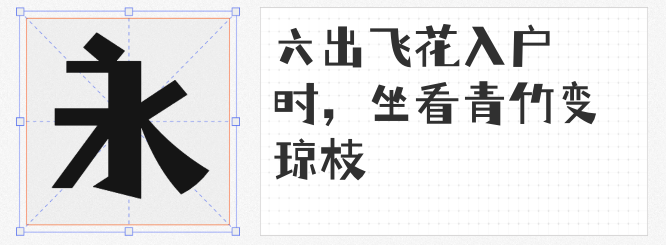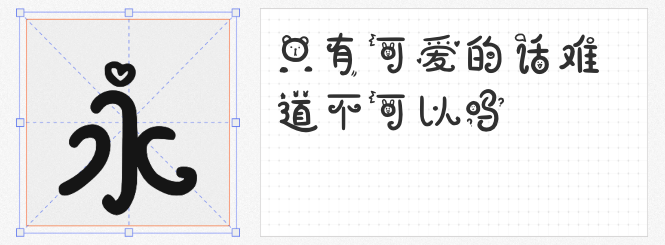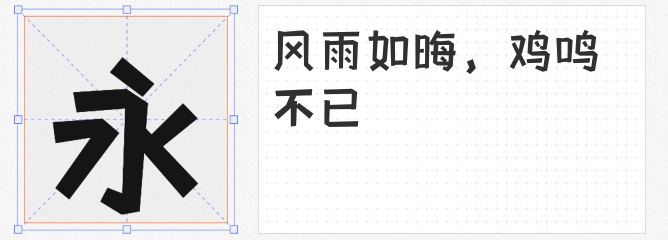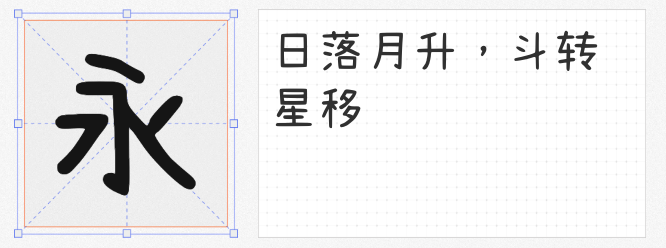
在追求个性与趣味的设计领域,一款灵动的字体往往能成为视觉焦点。今天为你精选四款自带可爱BUFF的免费商用创意字体,它们或古灵精怪,或软萌讨喜,轻松为设计注入鲜活生命力。
1.摄图摩登小方体
这款由摄图网与iFonts联袂打造的公益字体,将科幻片的未来感揉进黑体基因。方正笔画中暗藏太空舱般的几何细节,负形空间经过精妙切割,如同宇航员头盔的透明面罩,让文字既稳重又不失呼吸感。粗度适中的笔画既能驾驭电商大促的霓虹灯效,也能化身美食菜单的可爱招牌,是穿梭于现实与未来的设计多面手。
2.仓耳小丸子
当字体开始"表演",设计便成了游乐场。仓耳小丸子用夸张的粗细对比打破常规,某些笔画突然"叛逆"地歪斜,字间距也任性缩放,仿佛字体在纸面上跳踢踏舞。这种打破秩序的天真感,特别适合儿童绘本、文创周边等需要"不规则快乐"的场景,让观者一眼沦陷于它的古灵精怪。
3.千图小兔体
设计师将软萌兔耳化作笔画装饰,每个字都像是会跳动的棉花糖。免费下载的福利标签,让它成为独立设计师的宠儿——从奶茶店招牌到少女风海报,圆润线条自带甜蜜气息。最妙的是藏在小兔元素里的彩蛋:放大细看,某些笔画里藏着胡萝卜图案的负形惊喜。
4.cjkFonts全濑体
深度学习赋予这款字体"七十二变"的功力,既保留濑户体的手写温度,又通过算法生成全字符库。繁体、简体、日韩文字一网打尽,多语言混排时依然保持萌系调性。笔画转折处微妙的毛边处理,像是AI也学会了害羞脸红,适合需要跨文化卖萌的品牌设计。
这四款字体如同设计界的"可爱多",无论你是要打造会眨眼的LOGO,还是设计让人会心一笑的社交媒体配图,它们都能让创意如棉花糖般蓬松绽放。